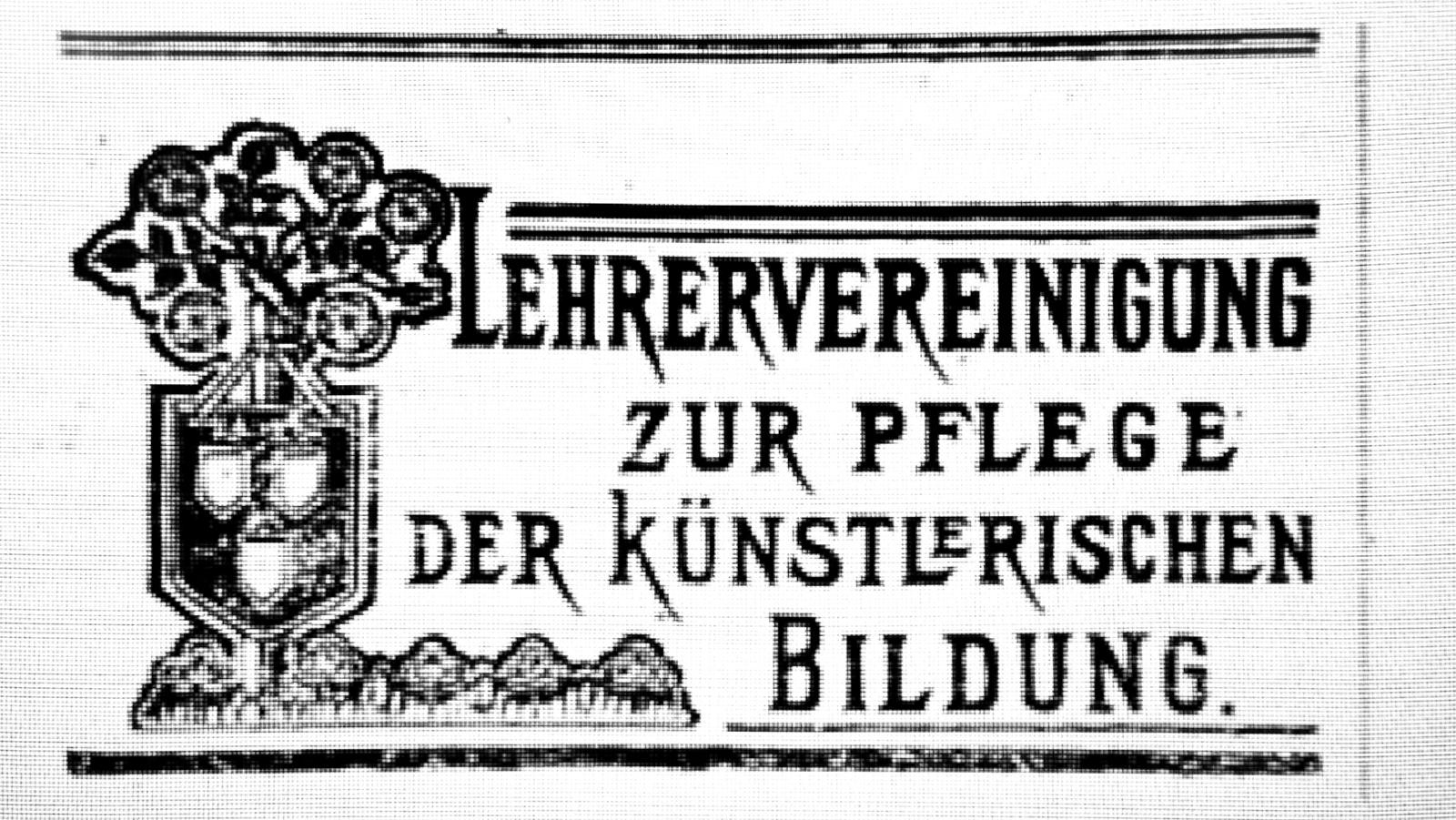
Welche Schrift/Digitalisierung? (Lehrervereinigung)
ich bin da über ein Bild gestolpert und möchte wissen, ob es die darauf zu sehende Schrift als digitale Schrift gibt? Bzw. ob es eine ähnliche gibt, ich hab leider nichts allzu passendes gefunden. Kann mir da eventuell jemand weiterhelfen?
Die Zeit: Anfang/erste Hälfte des 20. Jahrhunderts.
Da bin ich zu annähernd 100% davon überzeugt, das es weder eine Schrift in Blei, noch eine digitalisierung hiervon gibt.
Betrachtet man die jeweils gleichen Buchstaben, so fällt auf, dass diese in keinem Fall Deckungsgleich sind. Es handelt sich also mit an Sicherheit grenzender Wahrscheinlichkeit um eine handschriftliche Arbeit, und das Maler-Wappen deutet darauf hin,das dies wohl in einer entsprechenden Fachschule, möglicherweise als Schülerarbeit erstellt wurde, was mich die auch nicht so gut ausgeglichenen Buchstabenabstände vermuten lassen.
Auf genau diese Schrift habe ich sowieso nicht abgezielt (außer es wär der Fall gewesen, dass die Schrift auf dem Logo auf einer Bleisatsschrift basiert, welche jemand zufällig gekannt hätte). Die Grundsätze der "künstlerischen Bildung" der Zeit lassen ja sowieso vermuten, dass eher selbst etwas geschaffen wird, als existierendes zu verwenden...aber meine Hoffnung war nicht umsonst, die Rossano ist perfekt, vielen Dank!!
Die Grundsätze der "künstlerischen Bildung" der Zeit lassen ja sowieso vermuten, dass eher selbst etwas geschaffen wird, als existierendes zu verwenden
Ganz richtig, daher auch die große Bedeutung dieser Gruppe im Hinblick auf die Reform der Schulschriften — in Deutschland leider nicht ganz so geglückt, man hat ja Sütterlin statt Kuhlmann eingeführt, aber zumindest in Österreich hat sich Legrün durchgesetzt. :)
Das kann ein Stempel sein, der in "Pädagogische Reform" verwendet wurde … hier gibt’s das pdf der eingescannten Seite dazu.